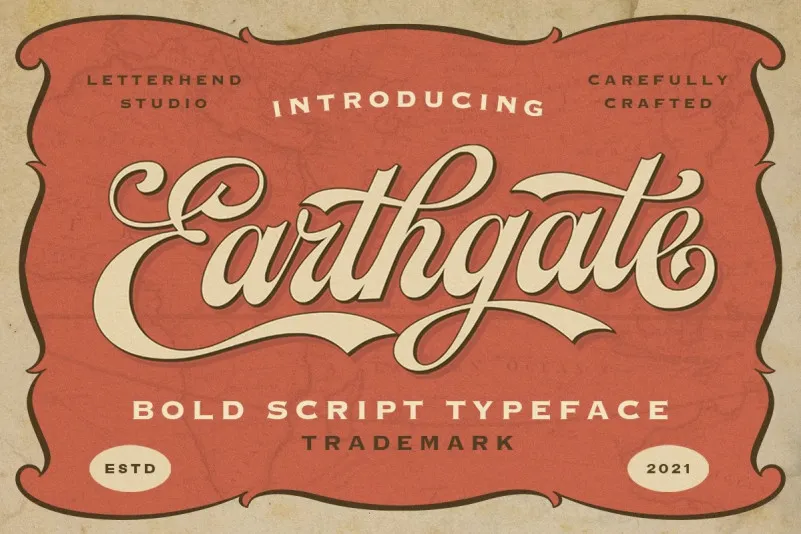
Earthgate Bold Script Font – Download Grátis
Earthgate Bold Script Font é uma tipografia de script inspirada nos estilos de design dos anos 70. Inspirado por esse movimento cultural que revolucionou as formas e cores, esta fonte carrega com ela um toque nostálgico, tornando-a perfeitamente adequada para projetos vintage ou retro. Suas curvaturas sutis e detalhes sofisticados criam uma identidade única para a fonte, permitindo que você crie letra vintage incrivelmente bonita apenas em segundos. Com seus traços suaves e estilo retrô, Earthgate Bold Script Font é ideal tanto para designers de jogos, como para aqueles criando arte digital vintage ou gráficos em estilo retro. Seja ele o próximo projeto da sua lista, certamente você encontrará nesta fonte uma maneira única de adicionar um toque nostálgico e alegre à sua arte.